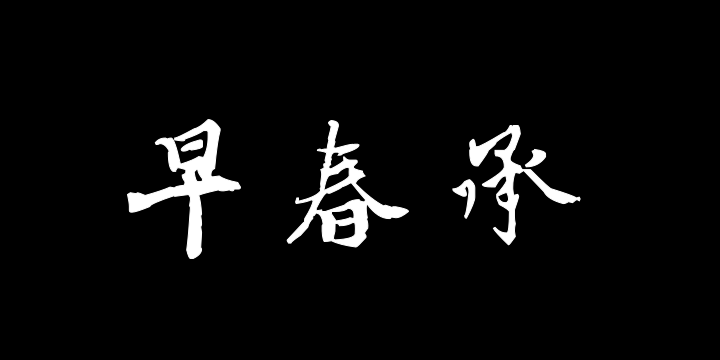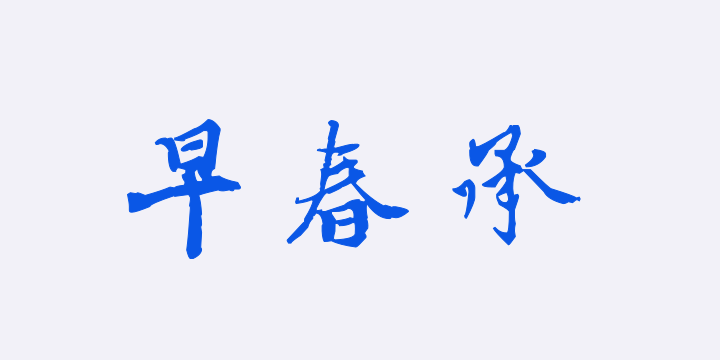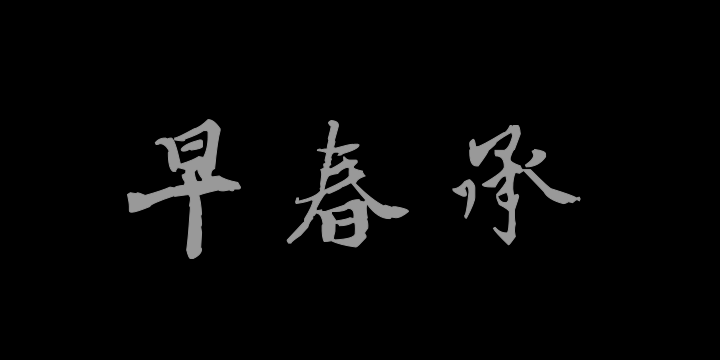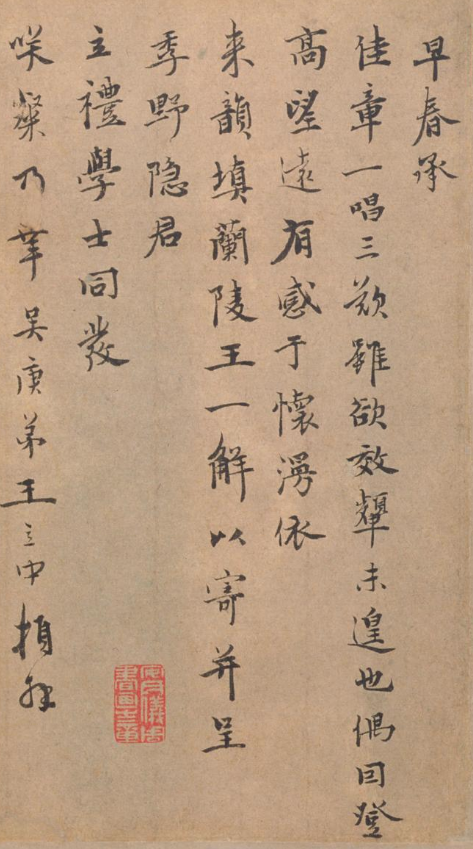
汉标王立中行书兰陵王词帖
关于汉标王立中行书兰陵王词帖字体字库信息
字体全名: 汉标王立中行书兰陵王词帖
铸字厂: 真迹小字库
字体简介: 下载须知:本字库非标准GB2312字库。本字库只包含了王立中《兰陵王词帖》真迹上的“249个字”。款钤 “王氏立中”、“彦强”二印。钤安岐、衡永等人鉴藏印。《兰陵王词帖》,元至正元年(1341年),王立中书。纸本,册页,纵27.2厘米,横43.4厘米。行书。此帖是王立中登高望远时,依“复儒翰学”来韵,填“兰陵王”一阕相赠,属文人诗词酬唱之作。“复儒翰学”指邵亨贞。邵氏亦长于填词,有《蛾术词选》四卷。王立中存世墨迹罕见,本帖书法取米芾结字的欹险,辅以平和质朴的笔致,自具一种散淡舒缓的意趣,与元末复古书势走向一致。